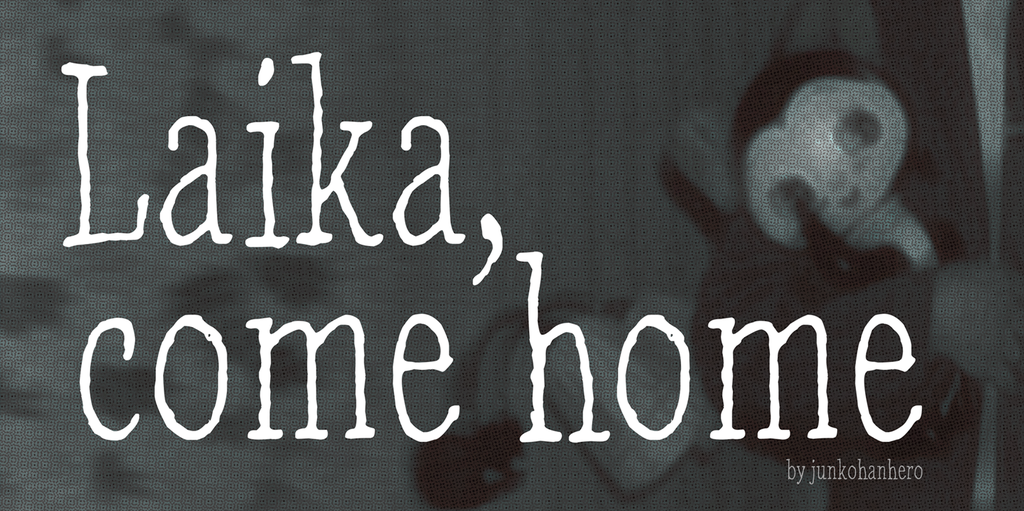
Estamos muito felizes por você escolher descarregar esta fonte ‘Laika, come home Font’. Ela é uma delicia para os olhos e tem um charme único que vai transformar qualquer projeto de escrita manuscrita personalizado em algo especial. A fonte foi projetada pelo designer Hamilton com um toque autêntico e natural, como se fosse assinado à mão. A escolha perfeita para gráficos e elementos de design onde você deseja que a mão do criador fale diretamente para o público. Não importa o seu projeto ou o seu estilo, a ‘Laika, come home Font’ é uma fonte escrita à mão perfeita para qualquer uso pessoal. Seu objetivo é fornecer um recurso gráfico grátis para quem deseja usar esta fonte de maneira personalizada para projetos pessoais. Se você quer usá-la em um projeto comercial, basta entrar em contato conosco. Você pode comprar a licença comercial pagando 15€ por e-mail através do PayPal, ou usando nosso botão de doação próximo à caixa de download. Somos muito contentes com cada doador regular que ajuda na manutenção da fonte e dos recursos criados pela Hamilton. Não importa quanto você possa contribuir, cada centavo faz uma grande diferença para o desenvolvimento desta fonte especial. Descarregue ‘Laika, come home Font’ agora e experimente a beleza única de um design que toca profundamente nossos sentimentos. Esperamos que ela se torne parte essencial do seu trabalho de design!